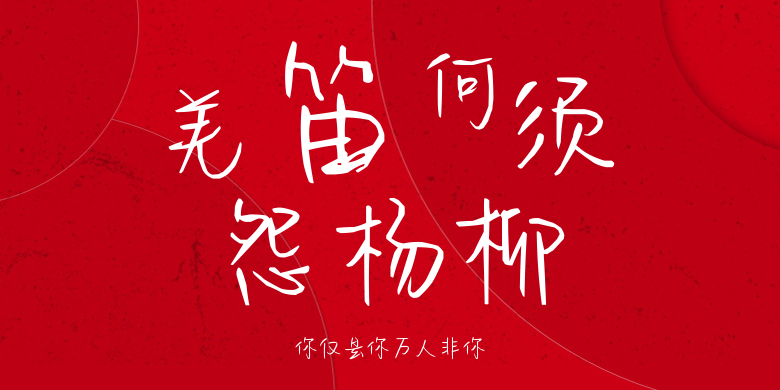
你仅是你万人非你
你仅是你万人非你,这款字体结构工整、笔画清晰,兼顾美观与易读性,适用于标题、正文、海报、包装、LOGO 等多种场景。字形优雅稳定,风格百搭耐看,适配日常排版与创意设计,让文字呈现更舒适、更具质感。你仅是你万人非你一笔一画,皆是细节,以均衡的比例、流畅的线条打造舒适视觉体验,字形端正大气,风格简约现代。无论是商业设计、品牌宣传还是日常排版,都能轻松驾驭,让文字更有格调与力量。你仅是你万人非你字体下载。